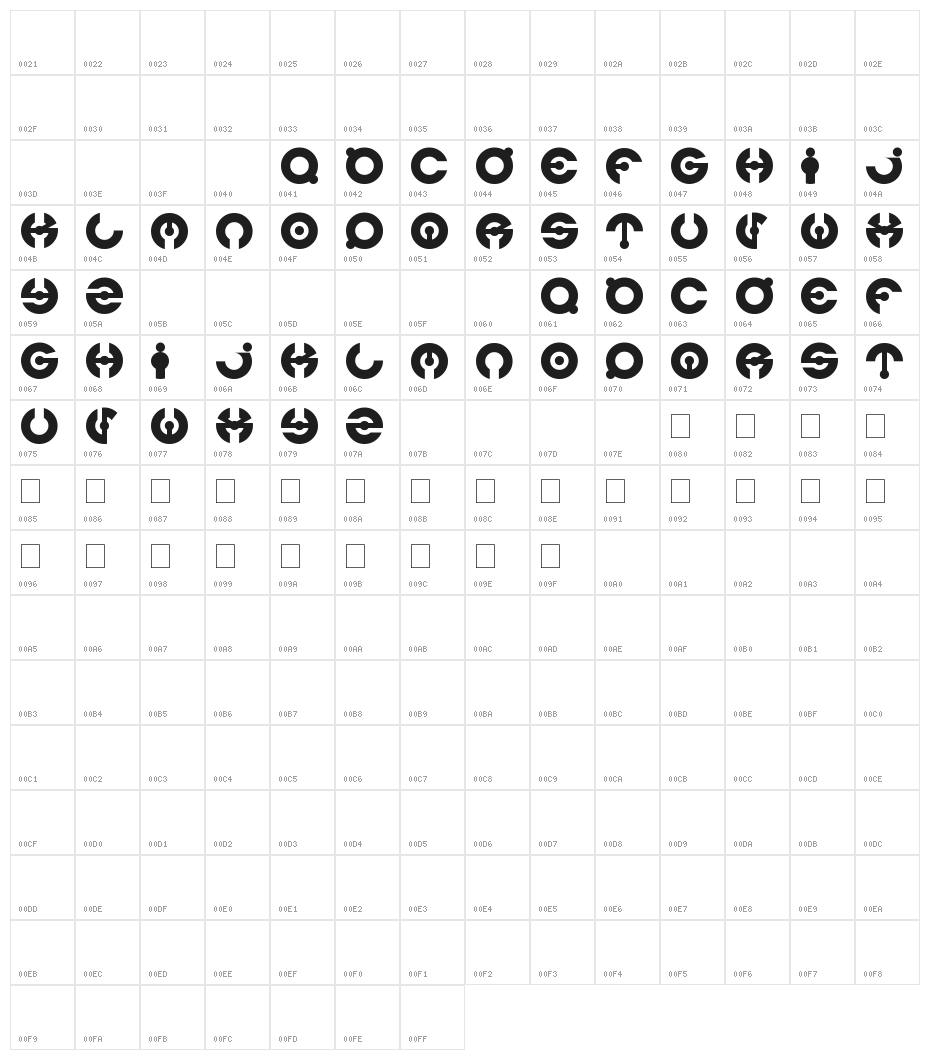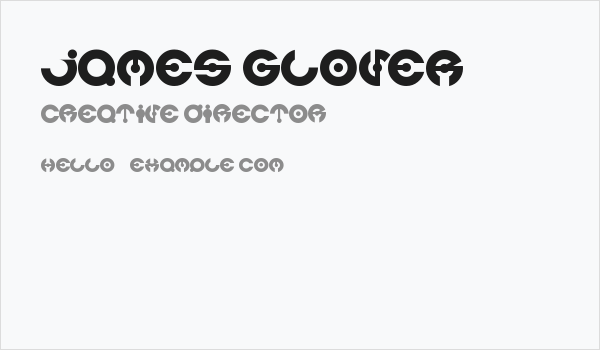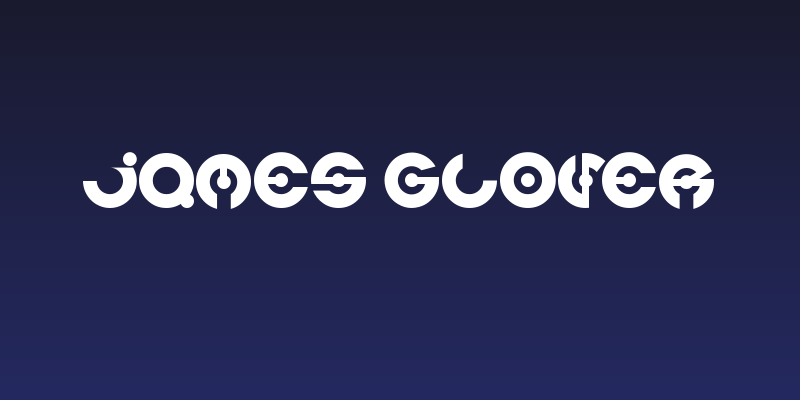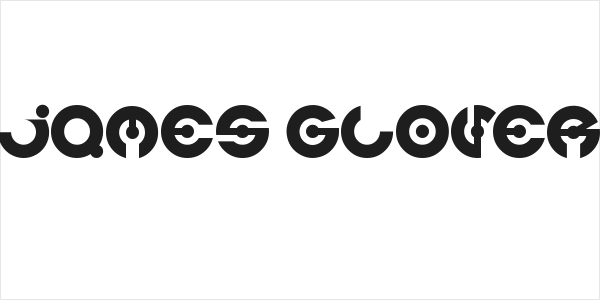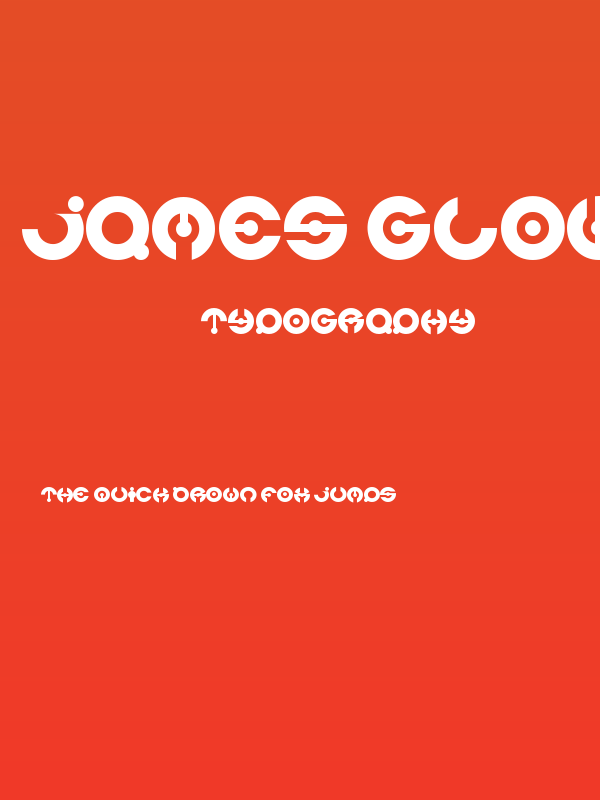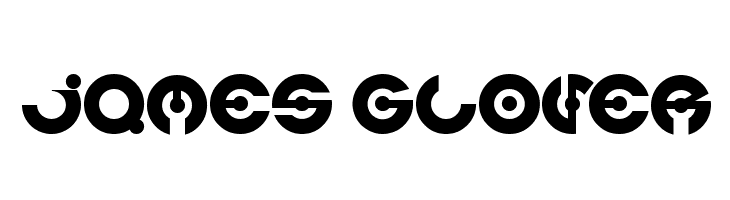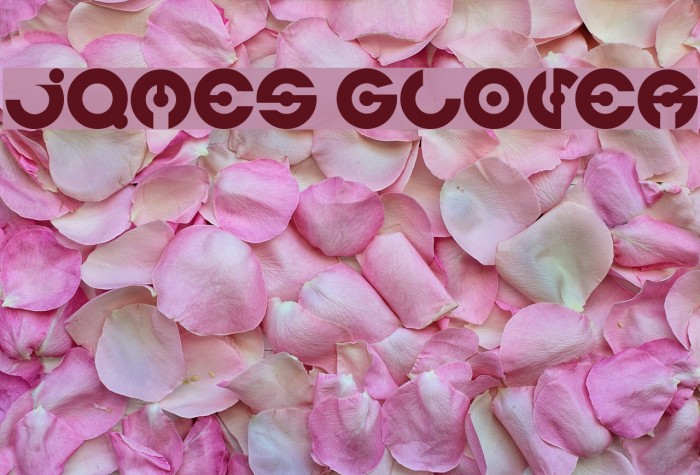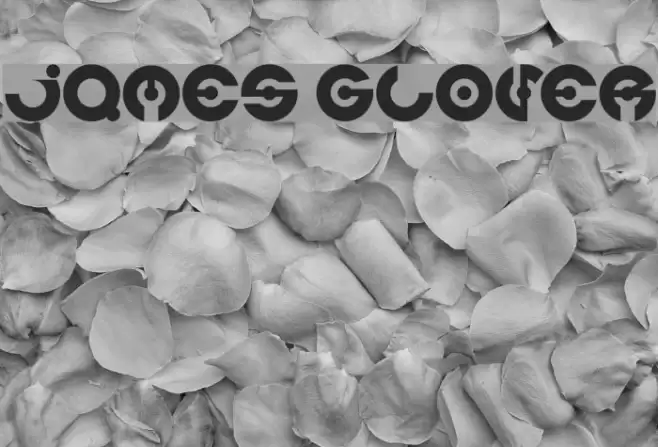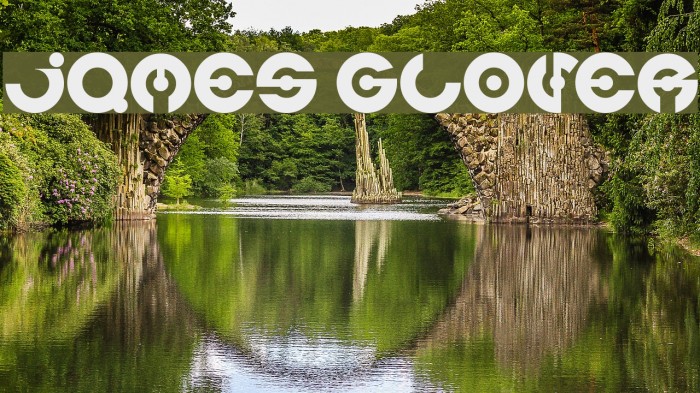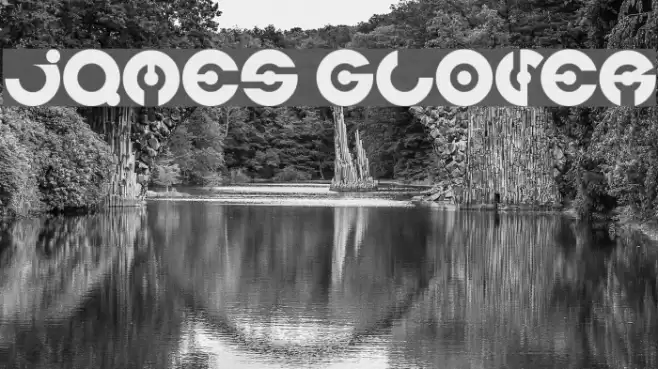
james glover Font
| Категория | Valentine |
| Общий стиль | Futuristic |
| Область применения | Logos, Headlines, Posters |
| Рекомендуемые проекты | Ideal for technology branding, sci-fi posters, video game titles, and modern logos. |